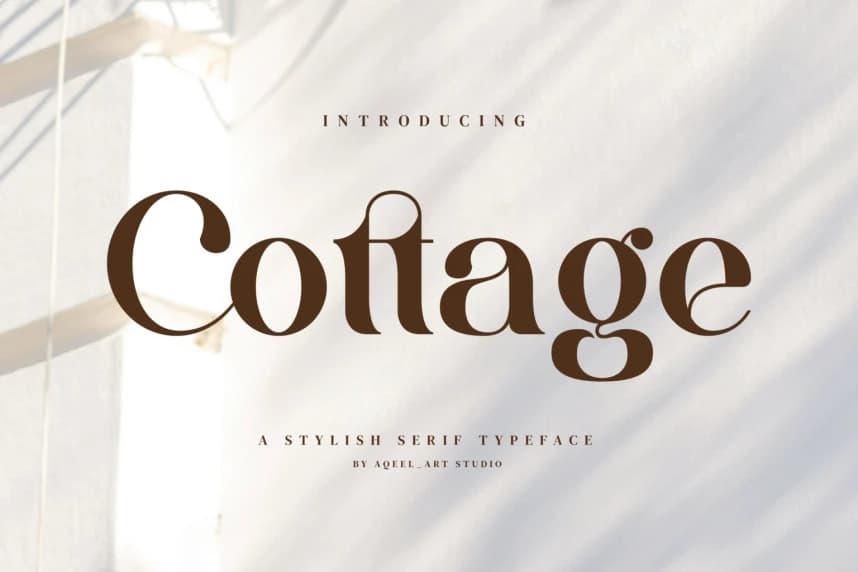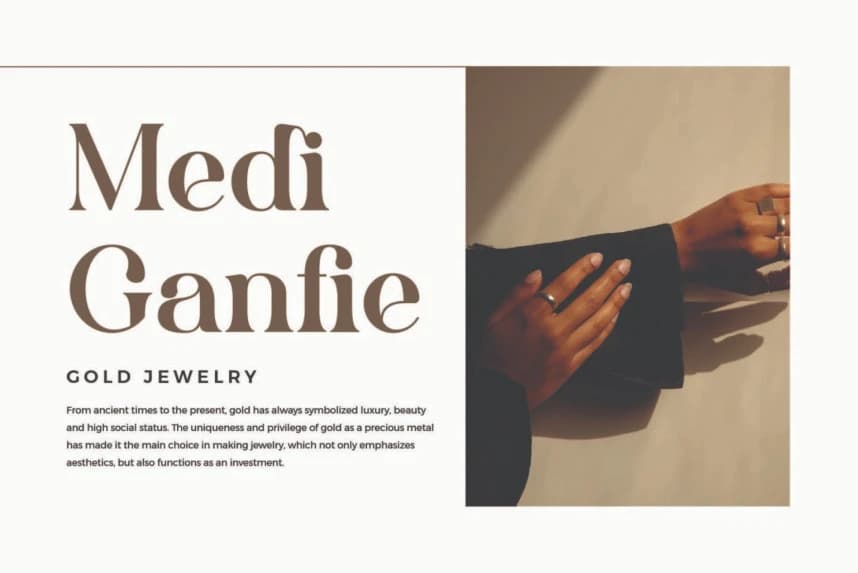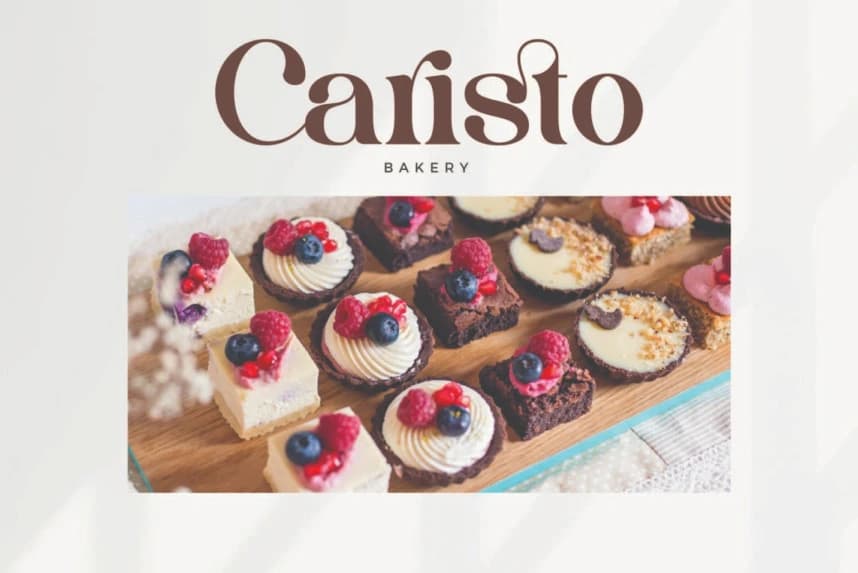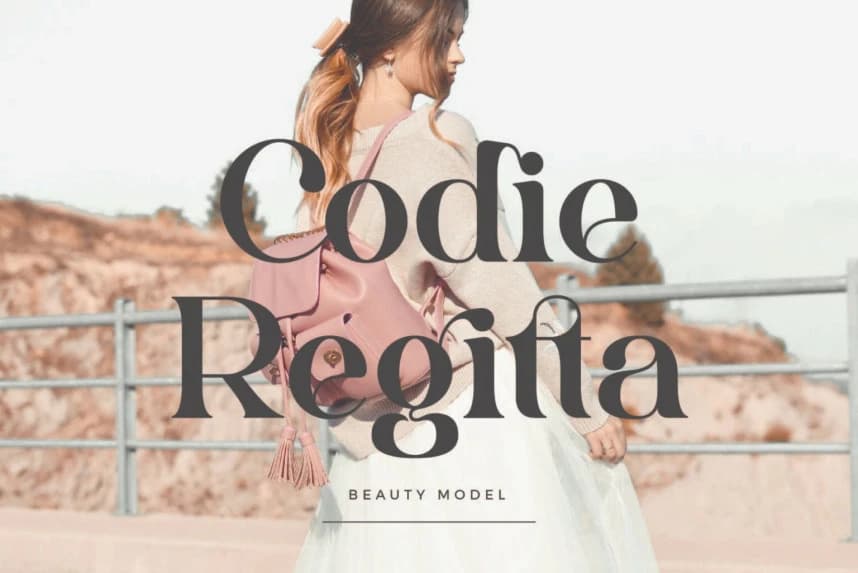
Cottage Font
Cottage Font - Şık Ligatür Yazı Tipi, ünlü minimalist logodan ilham alınmıştır; şablonlar, broşürler, videolar, reklam ve markalaşma için, logolar ve daha fazlasını tasarlamak amacıyla mükemmeldir.
Cottage Font - Stylish Ligature Typeface, ünlü minimalist logodan esinlenmiş, şablonlar, broşürler, videolar, reklam kimliği tasarımı, logolar ve daha fazlasını tasarlamak için ideal.